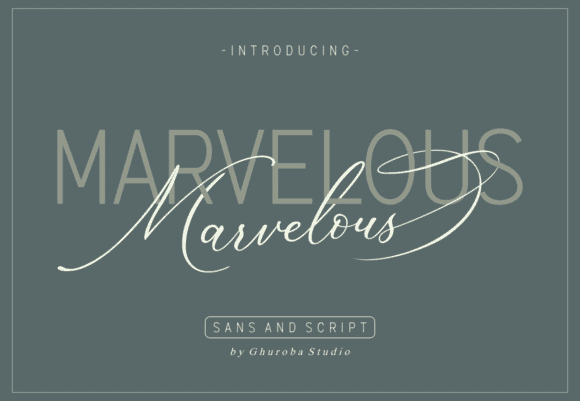
A Marvelous Font Duo é uma dupla única de fontes que une o sans serif estilizado e a escrita elegante num pacote perfeito para designers apaixonados por novas ideias. Esta dupla criativa foi projetada pelo designer zziplex, um artista digital que entremea formas modernas com riqueza visual. O conjunto da fonte Marvelous combina uma tipografia curta e contemporânea com uma escrita de estilo signature, criando um par perfeito para designers de marca, cartões de convite, cartazes empresariais, festas de casamento, logotipos, frases motivacionais e embalagens de produtos. A combinação única dessas duas fontes oferece aos designers a flexibilidade necessária para criar uma variedade impressionante de propostas gráficas, combinando elegância com contemporaneidade. Seja para um design pessoal ou profissional, esta dupla será uma escolha segura para qualquer projeto visual que busque transmitir elegância e simplicidade moderna.